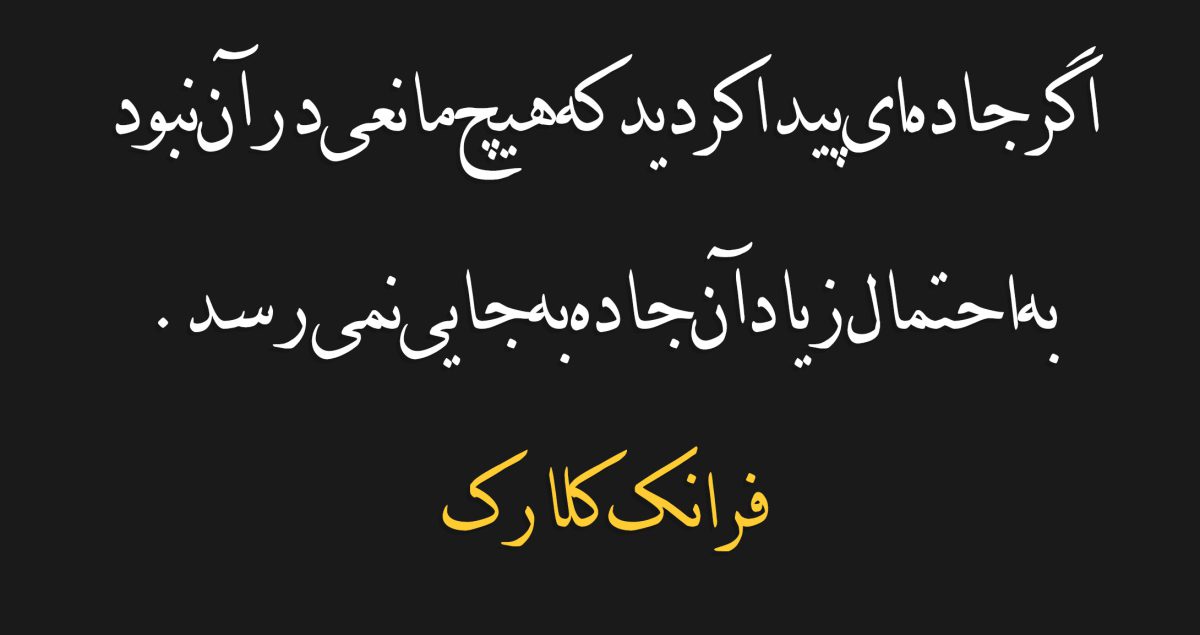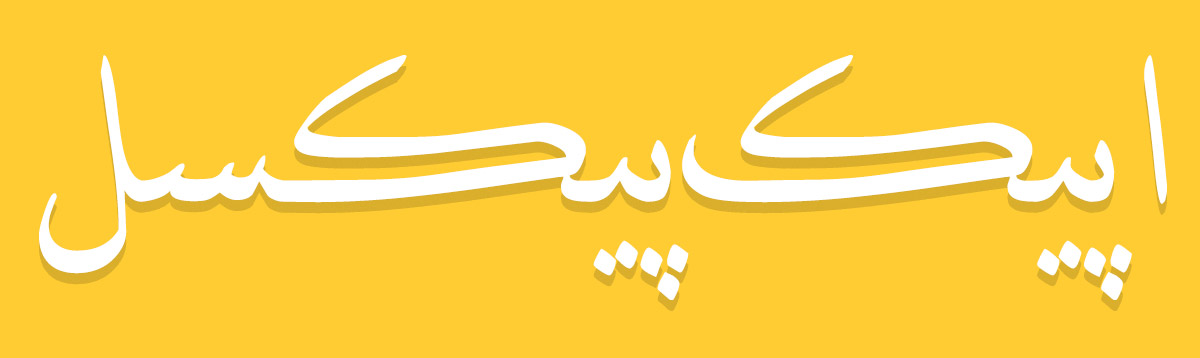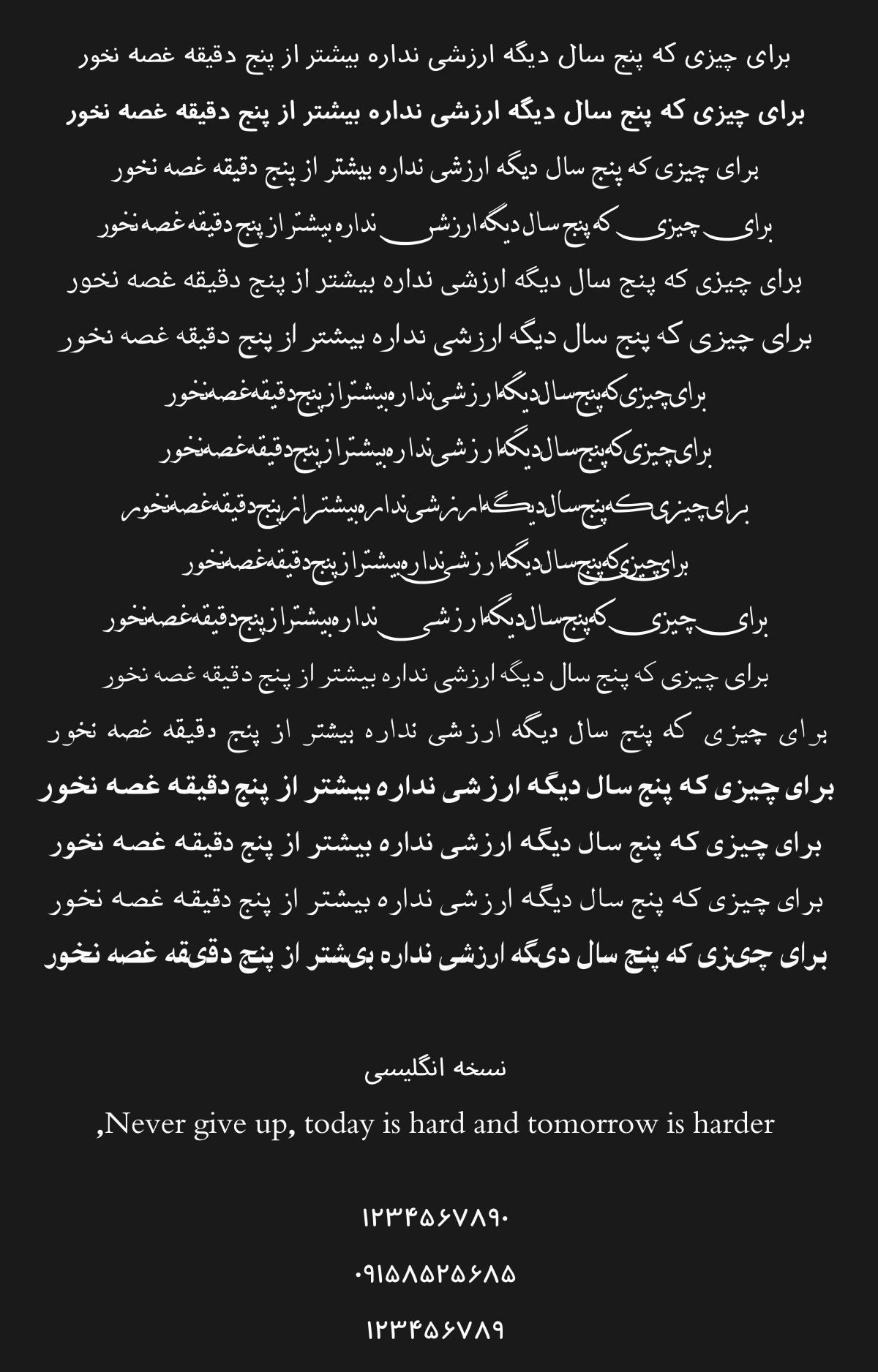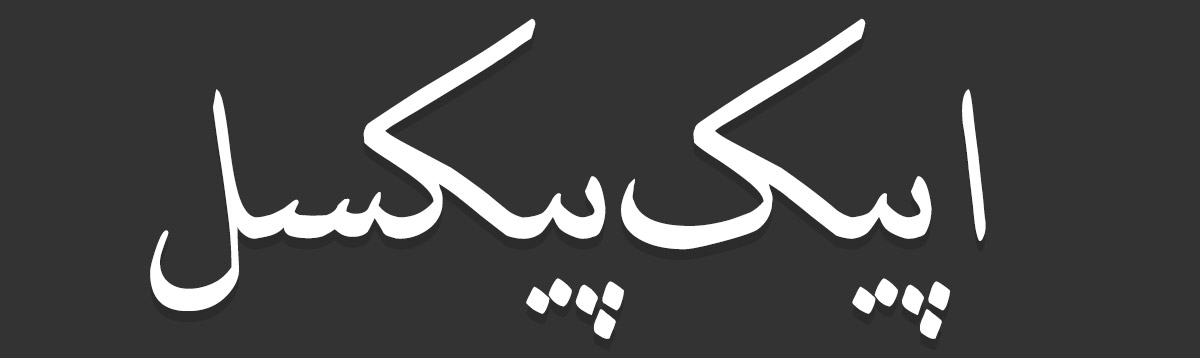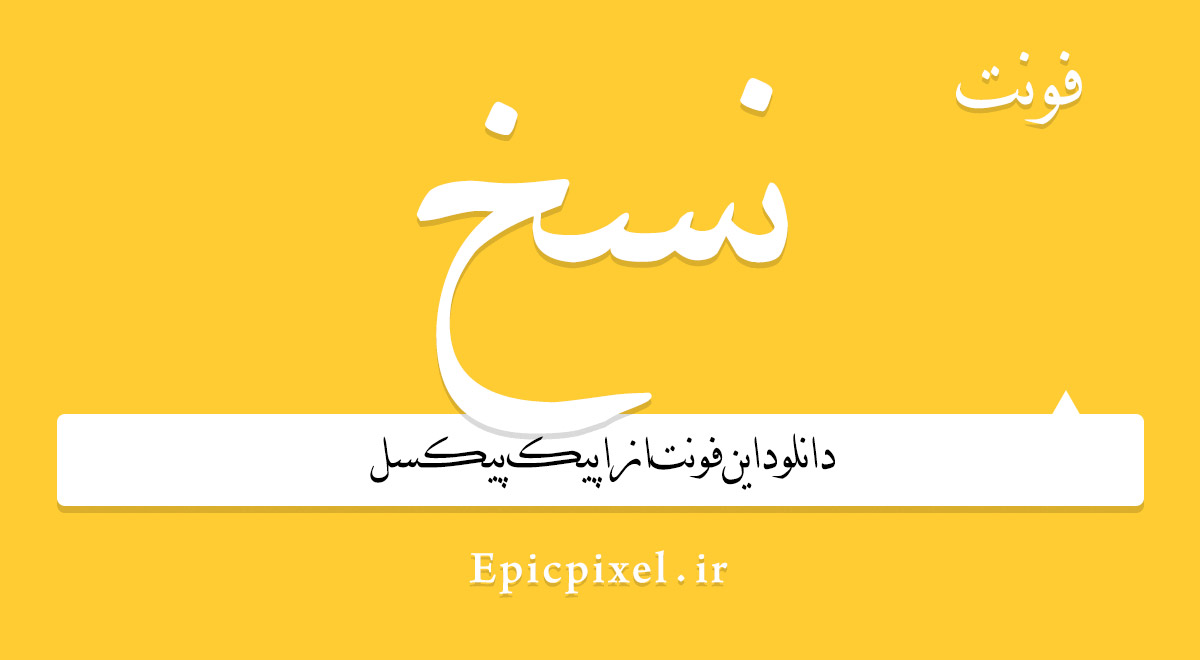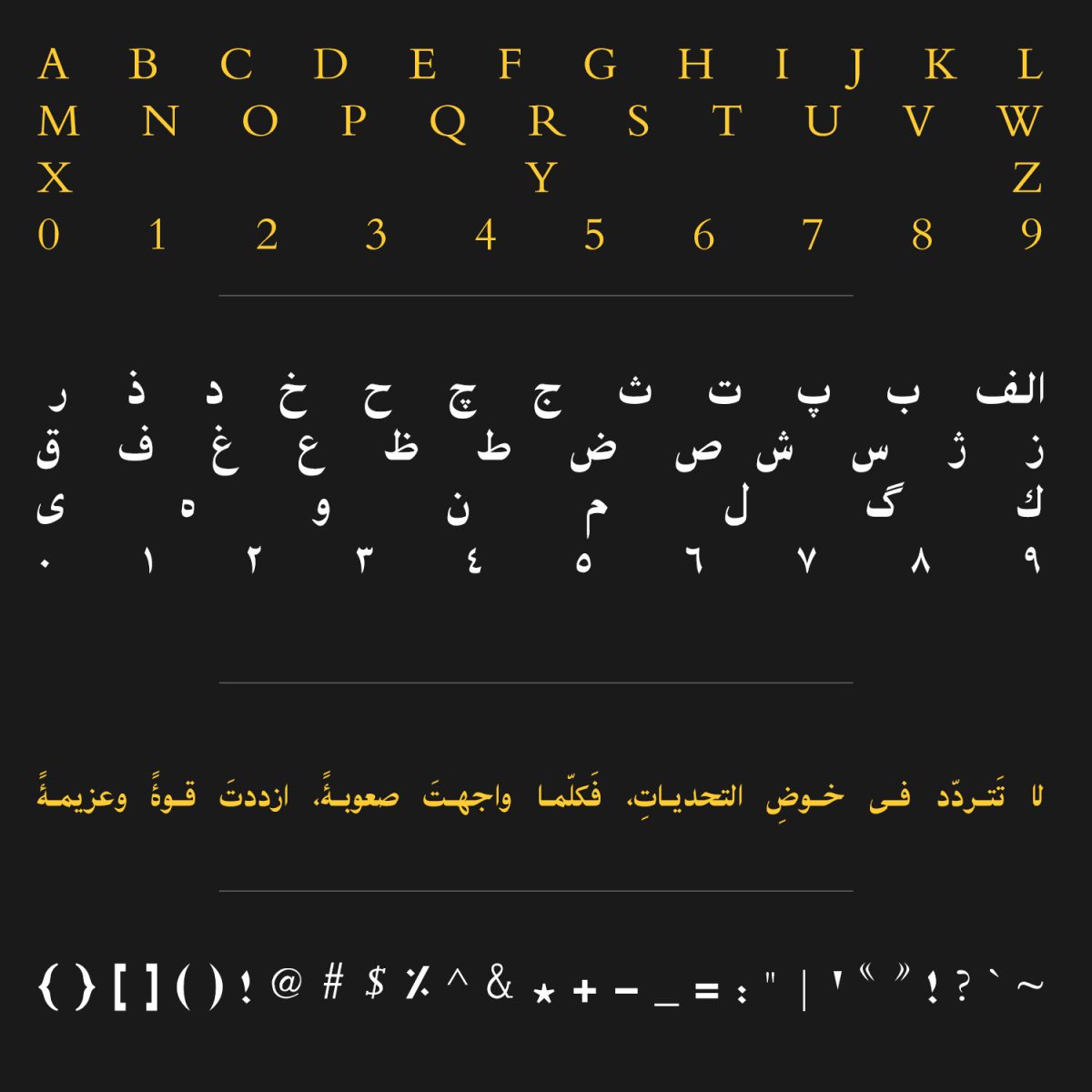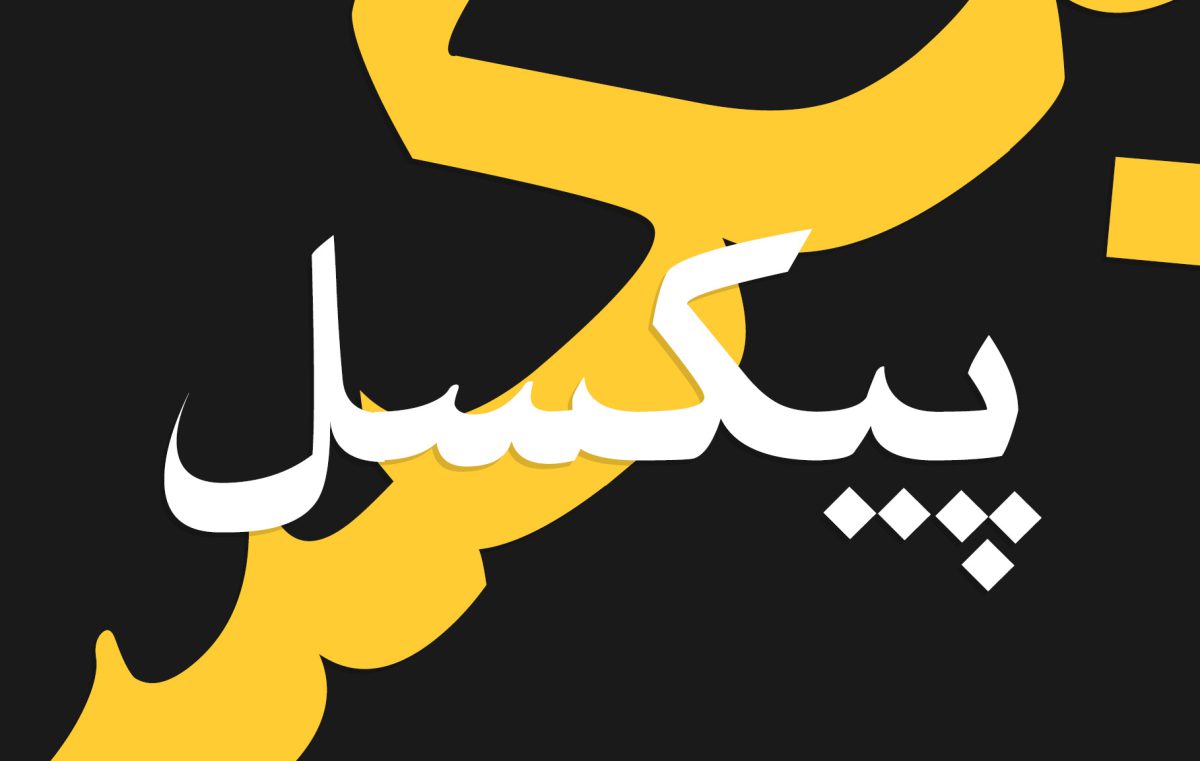
دانلود پکیج و مجموعه کامل فونت نسخ فارسی، آرشیوی گسترده شامل حدود + 41 فونت بر اساس خط نسخ است که به دلیل خوانایی بالا و مناسبت برای تحریر و نوشتن متون شناخته می شود. خط نسخ توسط ابن مقله شیرازی ابداع شده و برای نسخه برداری متون، به خصوص کتابت قرآن، به کار می رفته است. این مجموعه فونت شامل پیاده سازی های متنوعی از خط نسخ با نام های مختلف (مانند ادوبی نسخ، ایران نسخ، نسخ عزیز و غیره) است. مجموعه برای دانلود در دسترس بوده، در فرمت های ttf و otf ارائه شده و در تمام پلت فرمها شامل تمامی نسخه های ویندوز، ios، اندروید، وب و… و نرم افزارهای مختلف قابل استفاده است و زبان های فارسی، عربی، اردو و کردی را پشتیبانی می کند.
دانلودمجموعه کامل فونت های نسخ: خواناترین خط خوشنویسی اسلامی برای تحریر و طراحی
پکیج و مجموعه کامل فونت نسخ فارسی (Naskh)، آرشیوی گسترده و جامع برای طراحان، نویسندگان و علاقه مندان به استفاده از خط نسخ در محیط دیجیتال است. این مجموعه شامل فونت هایی است که در نام خود کلمه “Naskh” را دارند و در آن ها سبک نوشتاری نسخ رعایت شده است و به عنوان مجموعه کامل با حدود + 41 فونت ارائه شده است.
خط نسخ، یکی از شیوه های نگارش خط در خوشنویسی اسلامی است که در اوایل قرن سوم هجری قمری توسط ابن مقله شیرازی (ابوعبدالله محمد ابن حسین ابن مقله بیضاوی) ابداع شده یا به کمال رسیده است. نسخ یعنی نسخه برداری یا رونوشت کردن، و خط نسخ در واقع اولین خطی بود که برای تکمیل کردن نواقص و اشکالات خط کوفی و اضافه کردن اعراب و حرکات و آواها اختراع شد و آموختن و نوشتنش به مراتب سهل تر و آسان تر از خطوط قبلی بود. ابن مقله از روی خط نسخ شیوه های پنجگانه ی دیگری نیز ابداع کرد (ریحان، ثلث، رقاع، توقیع، محقق) برای مصارف خاص (نوشتن قرآن، تعلیم، نامه های دیوانی، تفسیر/حدیث، فرمان ها، اشعار/قصاید). خط یا فونت نسخ تابع خط ثلث است. از نظر تاریخی، خط نسخ بطورکلی از اواخر قرن دوم هجری رایج شد و به تمام سرزمین های شرقی که تحت لوای اسلام بودند، گسترش یافت. ایرانیان نیز نوع خاصی از نسخ را برای کتابت به کار می بردند. امتیاز مهم خط نسخ در رعایت نسبت است، که یکی از قواعد مهم خوشنویسی است و موجب زیبایی خط و خوانایی بالای آن می شود. از سده پنجم هجری تاکنون در کتابت قرآن اغلب از همین خط استفاده شده است، که نشان دهنده اهمیت و خوانایی بالای آن است.
فونت های نسخ در این مجموعه، بر خلاف فونت های نمایشی که برای تیترنویسی مناسبند، برای تحریر و نوشتن متون بسیار مناسب است و امکان تایپ سریع و دقیق را فراهم می کند. از این فونت ها می توان برای تایپ متون فارسی و عربی استفاده کرد. برخی فونت ها در این مجموعه بسیار شبیه به فونت های نیریزی، نازنین، دعوت و… بوده و می توانند به عنوان مکمل در کنار این فونت ها مورد استفاده قرار گیرند.
این مجموعه فونت شامل پیاده سازی های متنوعی از خط نسخ با نام های مختلف است، از جمله: فونت ا نسخ تحریر بولد، فونت دروید عربیک نسخ رگولار، فونت ام جی نسخ تیتر ضخیم، دکوتایپ نسخ اکستنشن، دکو تایپ پروفشنال نسخ اسپشیال، ای نسخ قرآنی رگولار، فونت ایران نسخ، نسخ عزیز رگولار، ام جی نسخ تیتر اوتلاین بلد، ام جی نسخ تیتر سایه ضخیم، ام جی نسخی رگولار، فونت ام جی اریدی نسخ پلین، اریدی نسخ بولد، اریدی نسخ بلک، فونت ام آر تی نسخ تیتر بولد، ام آر تی نسخ تیتر اوت لاین بولد، ام آر تی نسخ تیتر شدو بولد، خرید فونت نسخی ریگولار MRT Naskhi Regular، فونت دبلیو نسخ برای اتوکد ریگیولار، دابلیو نسخ ۱ رگیولار، دبلیو نسخ کشیده ۲ رگولار، دبلیو نسخ ۳ رگلار، دبلیو نسخ ۴ رگیولار، دابلیو نسخ ۵ ریگولار، دبلیو نسخ ۶ رگولار، فونت نسخ دی تی پی، فونت دی تی پی نسخ، نسخ دی تی پی نسخ ۲، مجموعه نسخ دی تی پی نسخ ۳، دی تی پی نسخ ۴، دانلود فونت فارسی نسخ اف نرمال، فونت اف نسخ ۱ نورمال، اف نسخ ۲ نورمال، اف نسخ ۳ معمولی، اف نسخ ۴ نرمال، اف نسخ ۵ نورمال، اف نسخ ۶ معمولی.
یکی از فونت های کلیدی در این مجموعه، فونت ادوبی نسخ (Adobe Naskh) است که یکی از فونت های خوبی که بارها و بارها درباره آن سوال شده است می باشد. این فونت نسخ متوسط بسیار با کیفیت است و شامل صدها حرف ترکیبی که زیبایی خاصی به آن داده است. جزو فونت های محبوب است و در سال ۲۰۱۱ توسط یک شرکت بزرگ منتشر گردید. از تمام حروف فارسی، عربی، اردو، کردی پشتیبانی میکند و شامل تمام حروف لاتین هم وزن و هم اندازه ای است. حروف عربی آن توسط یک خطاط پاکستانی و حروف لاتین توسط طراحان مشخصی طراحی و پیاده سازی شده است. این قلم زیبا کاملا open type ساپورت است و از کرنینگ (فشردگی بین حروف) به خوبی پشتیبانی میکند. بسیار استفاده می شود در طرح های عکس نوشته، اگرچه در برخی تصاویر، طراحان حروف این قلم را با کمک نرم افزارهای گرافیکی ویرایش کرده اند.
کاربردهای مجموعه فونت های نسخ در طراحی و نگارش
با توجه به ویژگی های اصلی خط نسخ، از جمله خوانایی بالا و مناسبت برای تحریر و نوشتن متون، و تنوع ارائه شده در این مجموعه فونت های نسخ، کاربردهای آن در دنیای طراحی و نگارش بسیار گسترده است. این قلم ها برای تایپ متون فارسی و عربی در نرم افزارهای مختلف، کتابت قرآن و متون مذهبی، طراحی های مذهبی، پوسترها، اعلامیه ها و… بسیار مناسب هستند. همچنین در طرح های عکس نوشته، صفحه آرایی, عناوین سینما و تلویزیون, گوشی های هوشمند, فونت وب, نشر رومیزی، و ایجاد طرح های تایپوگرافی (چیدمان حروف) مورد استفاده قرار می گیرند. سازگاری با تمام پلت فرمها شامل تمامی نسخه های ویندوز، ios، اندروید، وب و… و نرم افزارهای گرافیکی و ویرایش متن، استفاده از این مجموعه را در پروژه های متنوع تسهیل می کند و امکان استفاده از این خط خوانا را در هر محیطی فراهم می آورد.